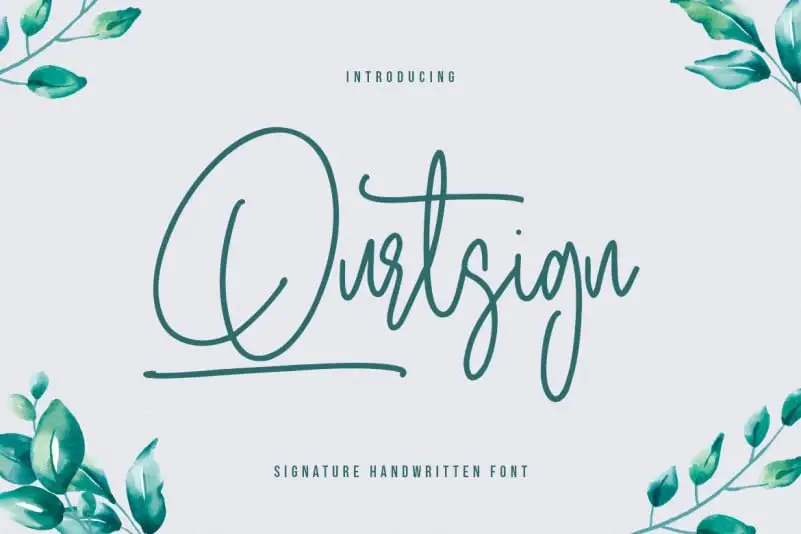
Qurtsign Signature Font
Aqui está uma descrição em português para a página de download da font ‘Qurtsign Signature Font’, seguindo as instruções fornecidas: Estou aqui a oportunidade de adicionar um toque autêntico à sua identidade visual com a Qurtsign Signature Font. Esta fonte script é uma preciosidade, projetada para imitar uma assinatura escrita à mão. Ela flui naturalmente enquanto você digita, mantendo-se fiel ao estilo da arte manual. O design é extremamente legível, mesmo que seu aspecto pareça muito contido. A Qurtsign não apenas enriquece a identidade visual de seus projetos, mas também assegura uma aparência única e autêntica – ideal tanto para assinaturas quanto para materiais de correspondência, logos, texturas tipográficas, citações, capas de revistas ou livros. Ela é perfeitamente adaptada para qualquer aplicação que você possa imaginar. Esta font é um domínio a mais na sua biblioteca de recursos gráficos, oferecendo uma solução versátil e profissional ideal para diversos formatos de mídia digital e impresso. Descubra o verdadeiro valor do trabalho manual em cada projeto, com a Qurtsign Signature Font.